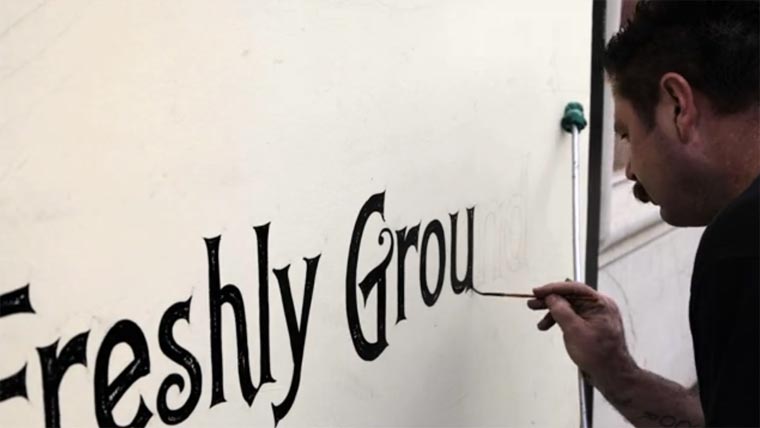
Kurzdoku über handgemalte Typografie keepers_of_the_craft
Sean Starr malt Schilder. Mit der Hand. Genauer gesagt Schriftzüge. Die Kurzdokumentation Keepers of the Craft – Traditional Sign Makers nimmt uns mit in den beruflichen Alltag des Inhabers von Starr Studios. Seit über zwanzig Jahren werden dort auf traditionelle Weise Firmenschilder und Schriftzüge kreiert. Handegemalt, versteht sich. Sehr beeindruckende Arbeit, vor allem, was Ruhe, Geduld und Präision anbetrifft. Und Hochachtung vor den Unternehmen, die nicht für ein paar Taler einen modernen Laserdruck erstellen lassen, sondern so etwas wunderbar Handgefertigtes erwerben. Jedenfalls eine sehenswerte Dokumetationspremiere von Nathaniel Day.